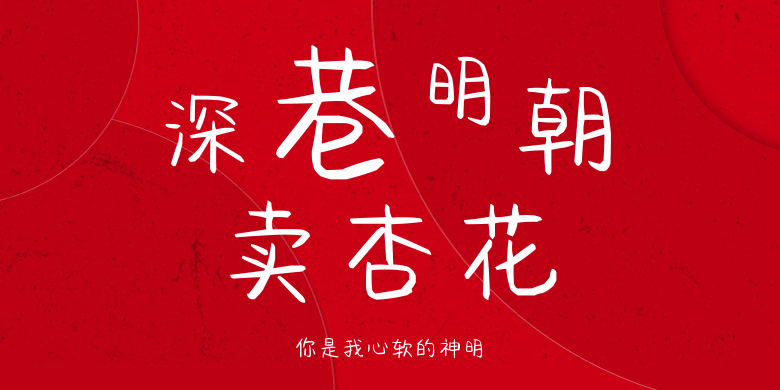
你是我心软的神明,这款字体结构工整、笔画清晰,兼顾美观与易读性,适用于标题、正文、海报、包装、LOGO 等多种场景。字形优雅稳定,风格百搭耐看,适配日常排版与创意设计,让文字呈现更舒适、更具质感。你是我心软的神明一笔一画,皆是细节,以均衡的比例、流畅的线条打造舒适视觉体验,字形端正大气,风格简约现代。无论是商业设计、品牌宣传还是日常排版,都能轻松驾驭,让文字更有格调与力量。你是我心软的神明字体下载。